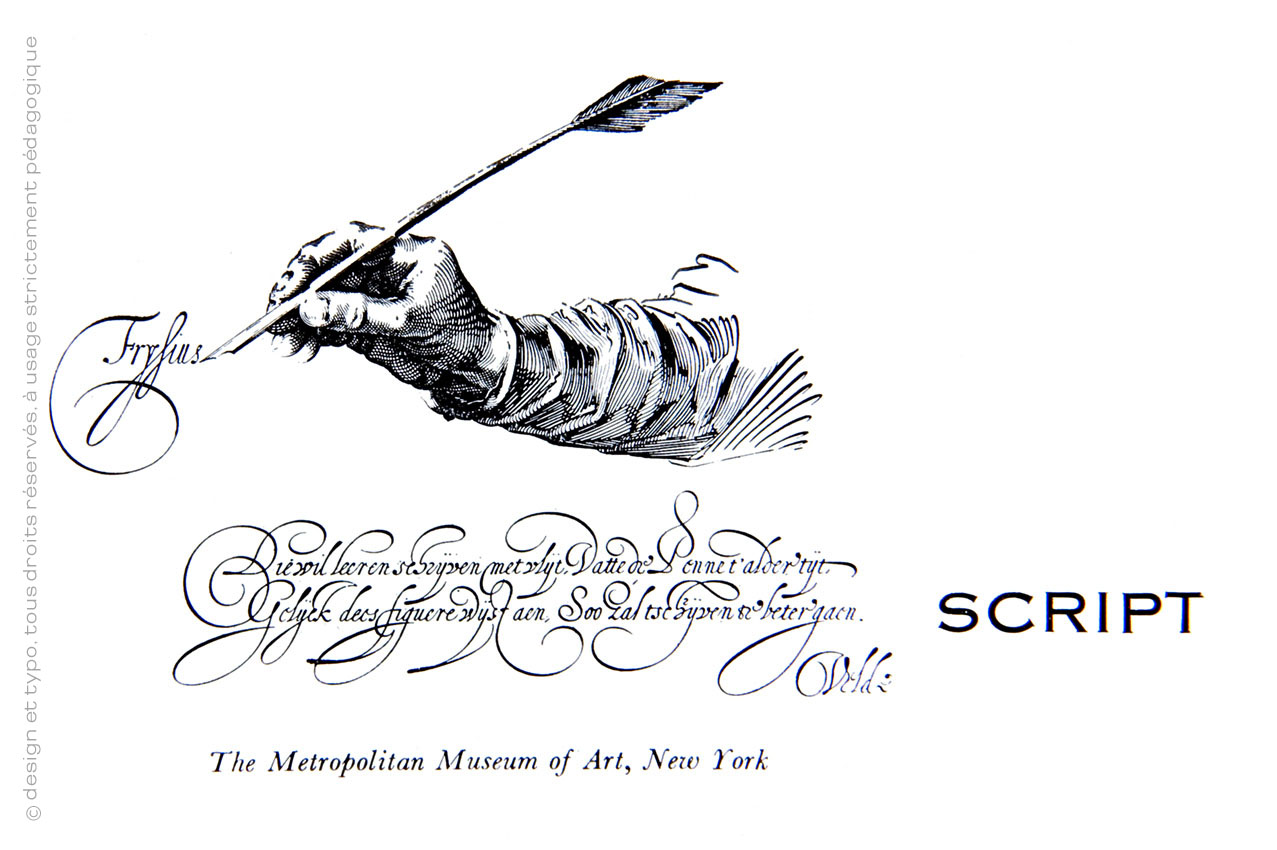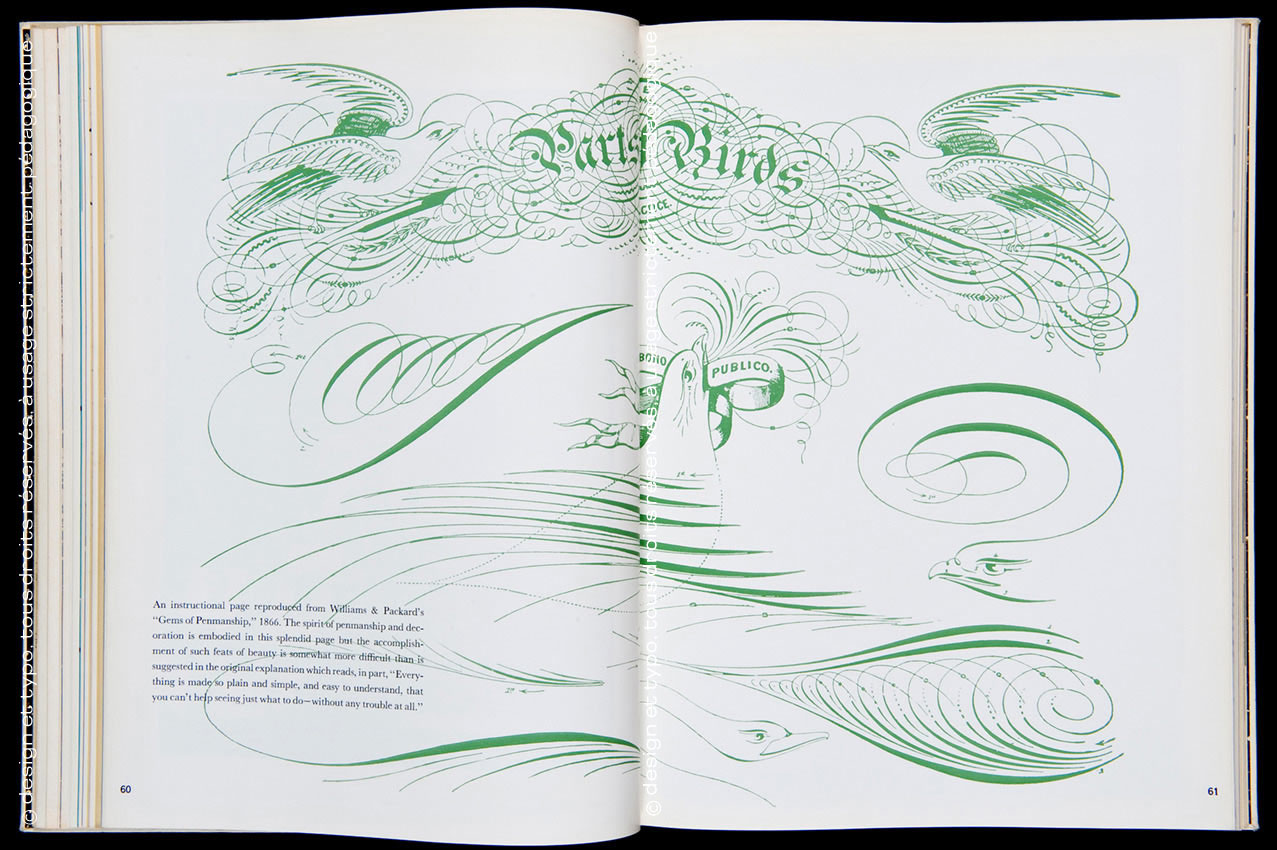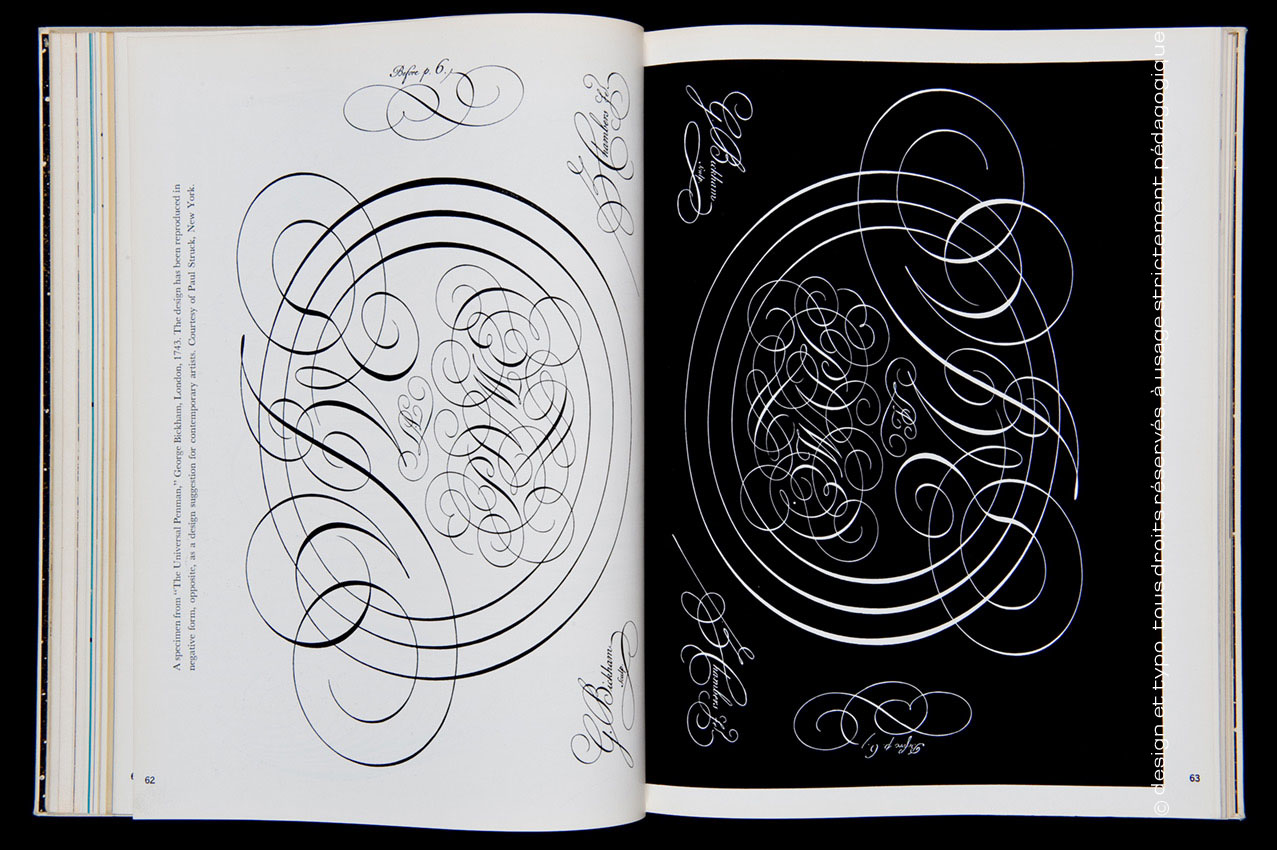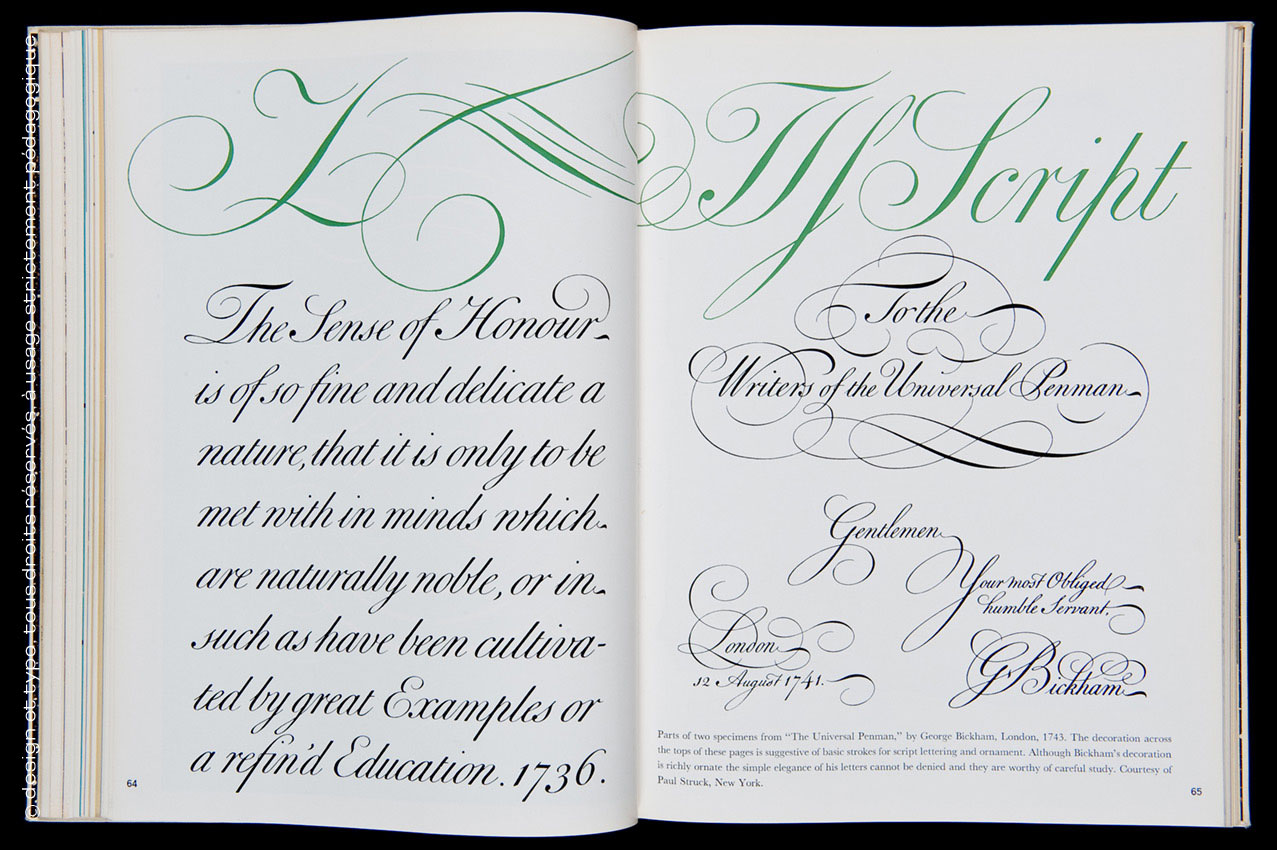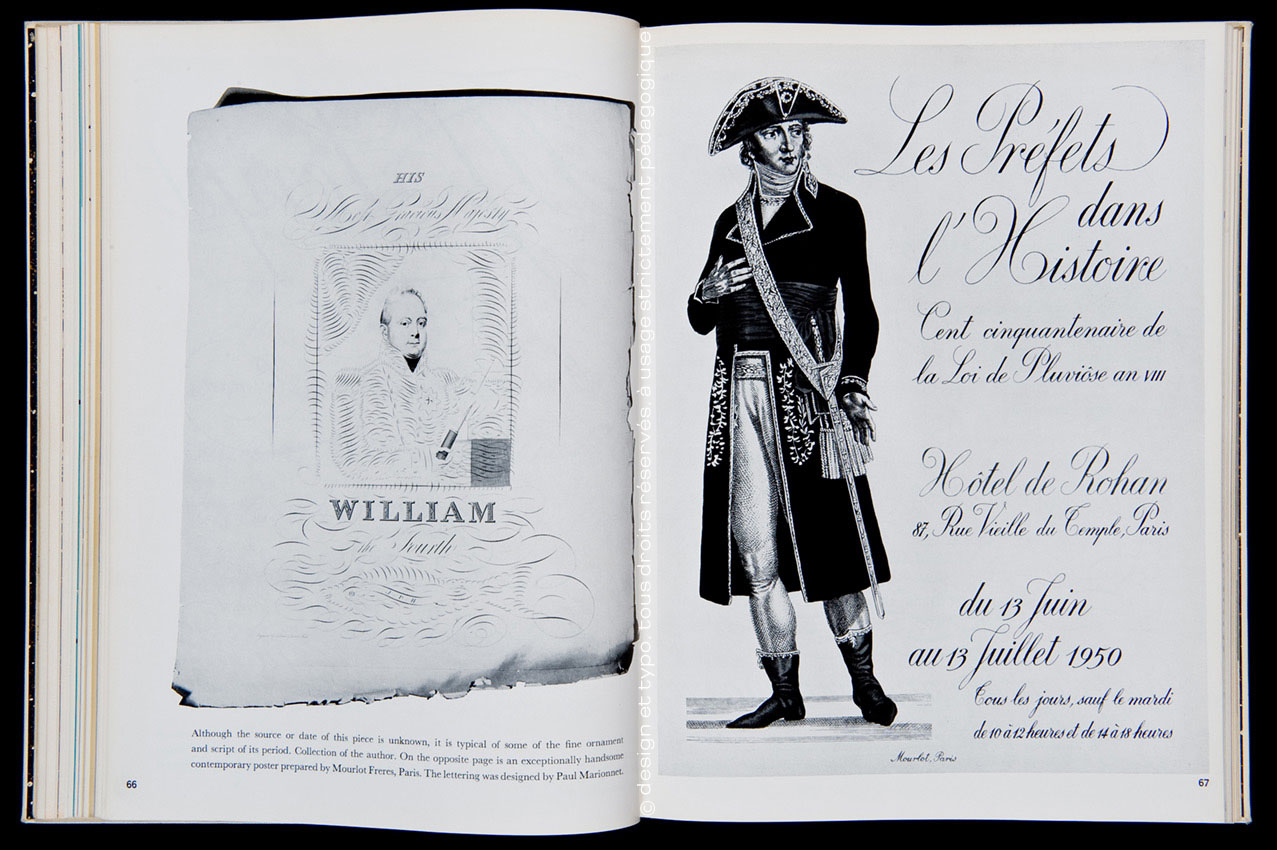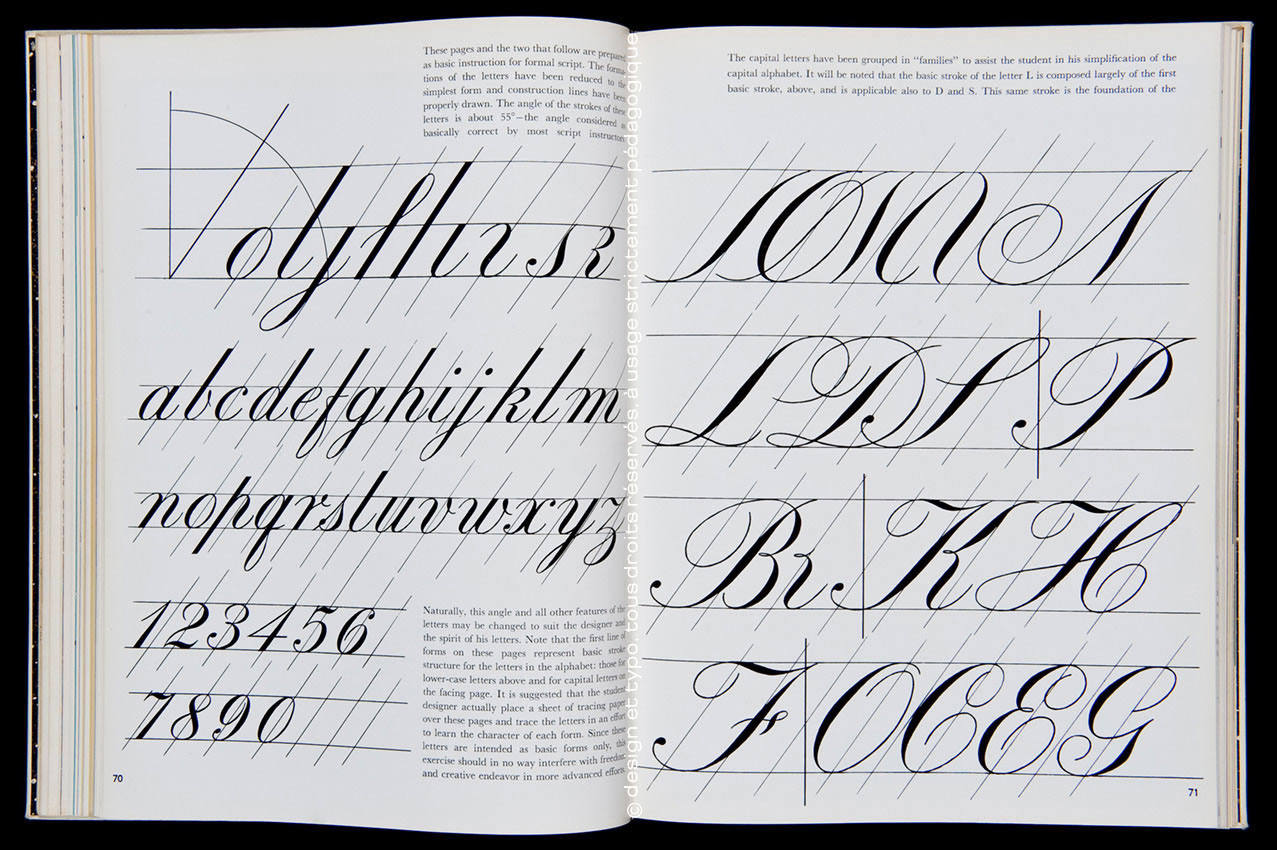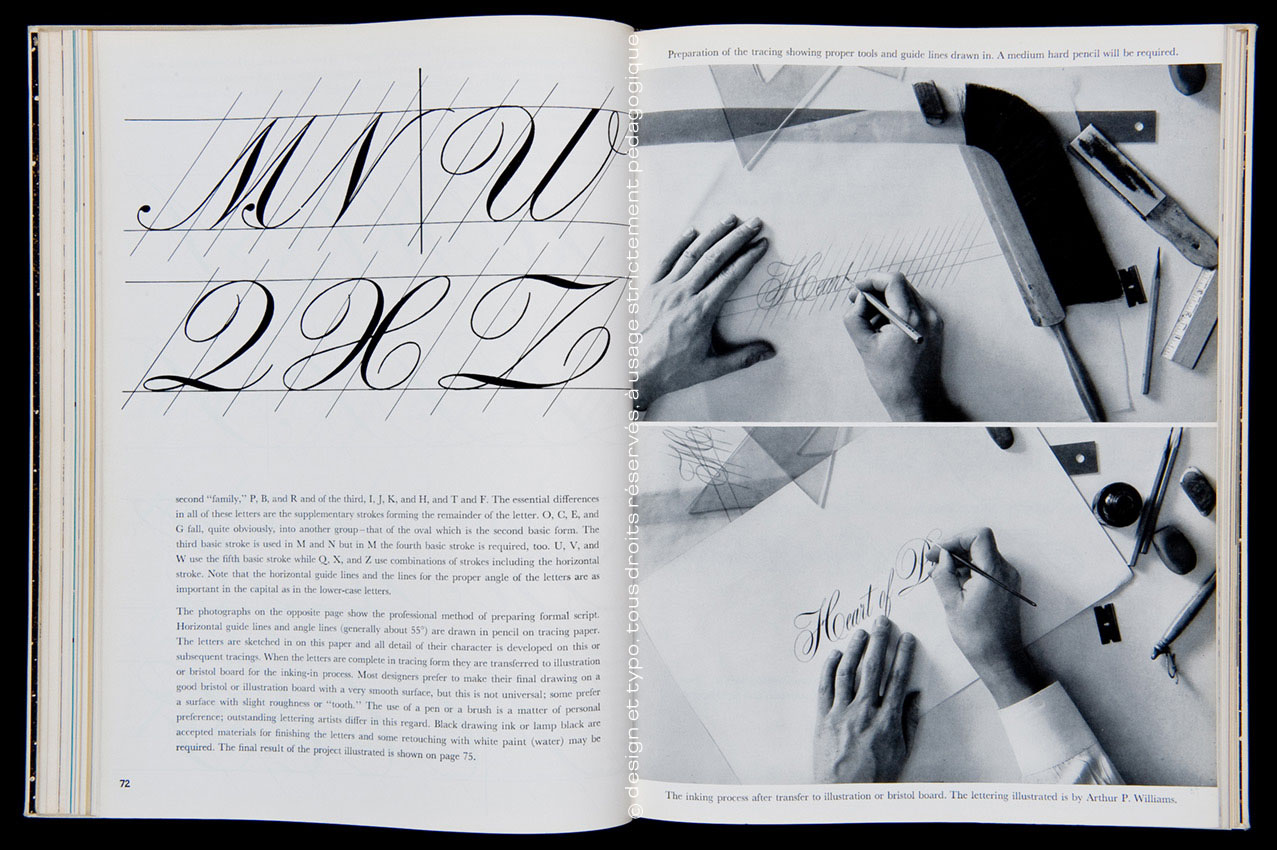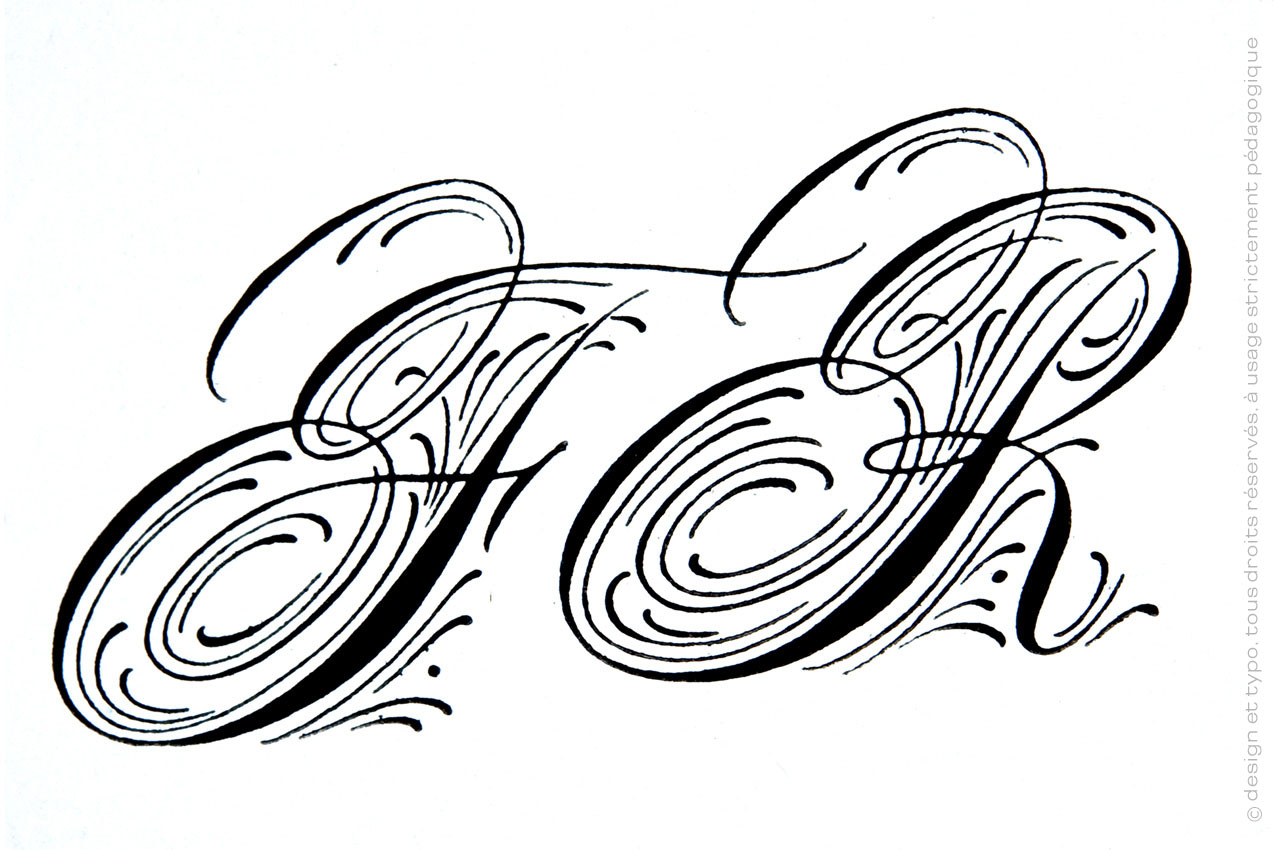
Typographie anglosaxonne et classification selon Raymond A.Ballinger (2/4)
C’est en 1952 que les éditions Reinhold Publishing Corp. ont publié cette magnifique «somme» de Raymond A.Ballinger. Celui-ci l’a dédicacé à sa maman, Mary Lizzie Ballinger et à son épouse Louise Bowen Bellinger.
L’édition que je vous montre là est celle, augmentée de 1956. L’objet du livre, et c’est sans doute là, où, on peut se poser des questions, est de tenter d’établir une sorte de classification des polices.
Bien entendu nous sommes juste avant l’explosion des polices de photocomposition et tout ce que vous allez découvrir dans ces colonnes a été composé soit en typographie plomb, soit en Ludlow, soit en phototitrage puisque cette technique, inventée en 1927 par Edward Rondthaler était déjà largement diffusée.
C’est-à-dire que nous sommes aussi avant les travaux de Maximilien Vox et d’Albert Hollenstein qui ont créé la fameuse classification Vox-Atypi. Alors qu’est ce qui fait l’intérêt de ce recueil de «poèmes» typographiques? Sans doute l’étendue des documents. Sans doute aussi le souci de l’auteur de ne rien oublier. Bien que, bien que. Nous sommes là en présence d’une classification américaine donc extrêmement réductrice là ou Vox et plus tard Allessandrini ont essayé de «décrypter» les familles de caractères selon des typologies beaucoup plus fines.
Mais l’ouvrage pose aussi la question suivante: quelle est la bonne manière de classer les caractères? Les américains ne s’embarassent pas de détails. Il y a les old styles, les modernes, les mechanical, les gothiques (nos bâtons ou linéales), les scripts et les fantaisies. Ne leur demandez pas (mille pardons mais je parle là des graphistes d’avant l’apogée du numérique dont l’apport culturel a fait bouger considérablement les lignes d’un savoir qui semblait déjà perdu pour tous), ne leur demandez pas, disais-je, d’essayer de comparer des humanes avec des garaldes ou des réales. Leur sens pratique leur font classer les polices, plus souvent en fonction de leur «graisse», qu’en fonction de la forme des empattements.
En tous cas, Raymond A.Ballinger avait déjà une vision assez moderne puisqu’il va terminer son ouvrage par un feu d’artifice de typographies expérimentales que je vous laisserai découvrir dans les derniers chapitres de cette chronique.